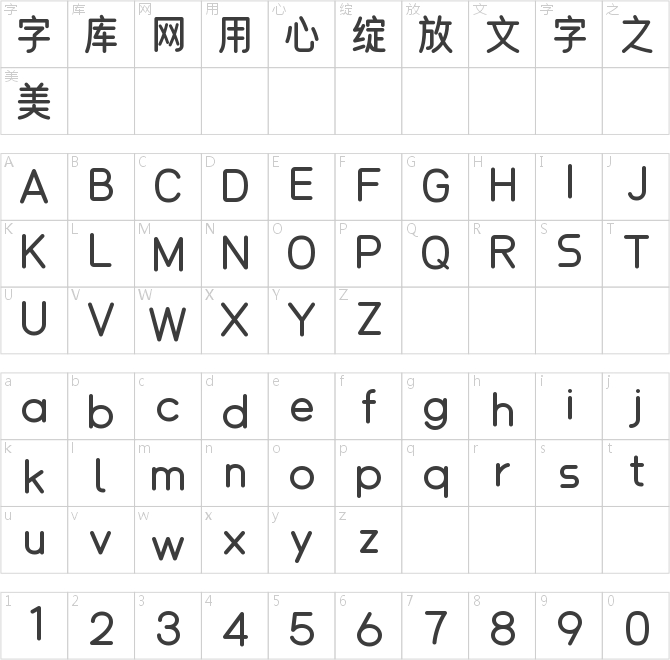
字体名称: 优设鲨鱼菲特健
优设鲨鱼菲特健康体
优设鲨鱼菲特健康体介绍
由字绘中国发起,新零售健康轻食品牌鲨鱼菲特联合优设与字由,为广大设计师特推出了一款专为健康而生,电商应用场景极强的优质字体——优设鲨鱼菲特健康体。
优设鲨鱼菲特健康体字体字库是一款让人赏心悦目、百看不厌的中文字体,适合各类广告和产品包装设计应用,字体大小3.13MB,格式为ttf字体,上传用户是/zyj【GF】,作者/版权方为优设